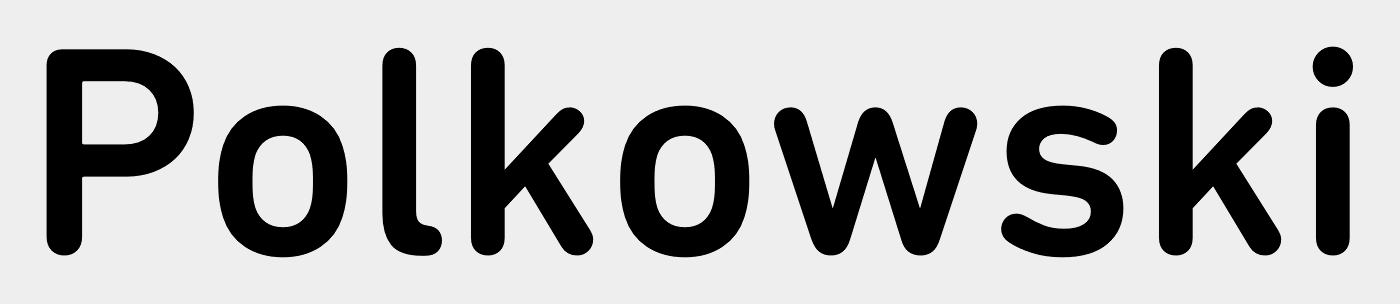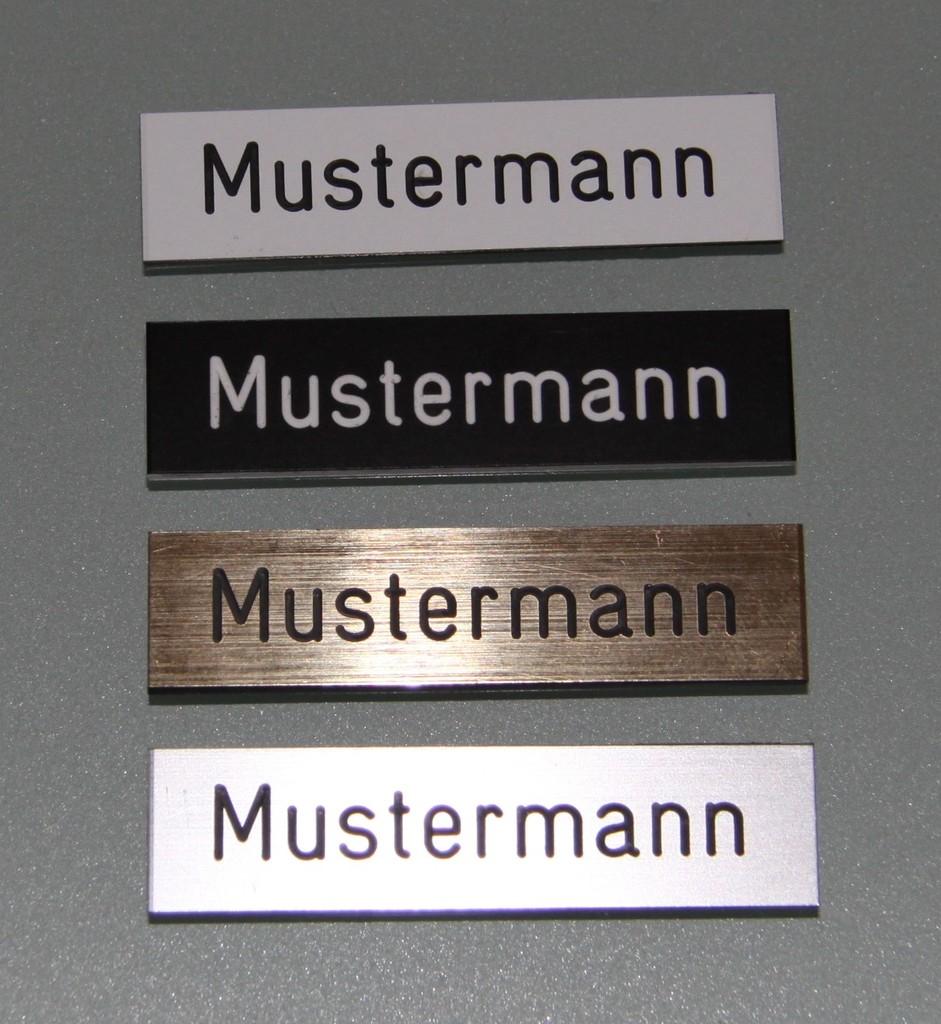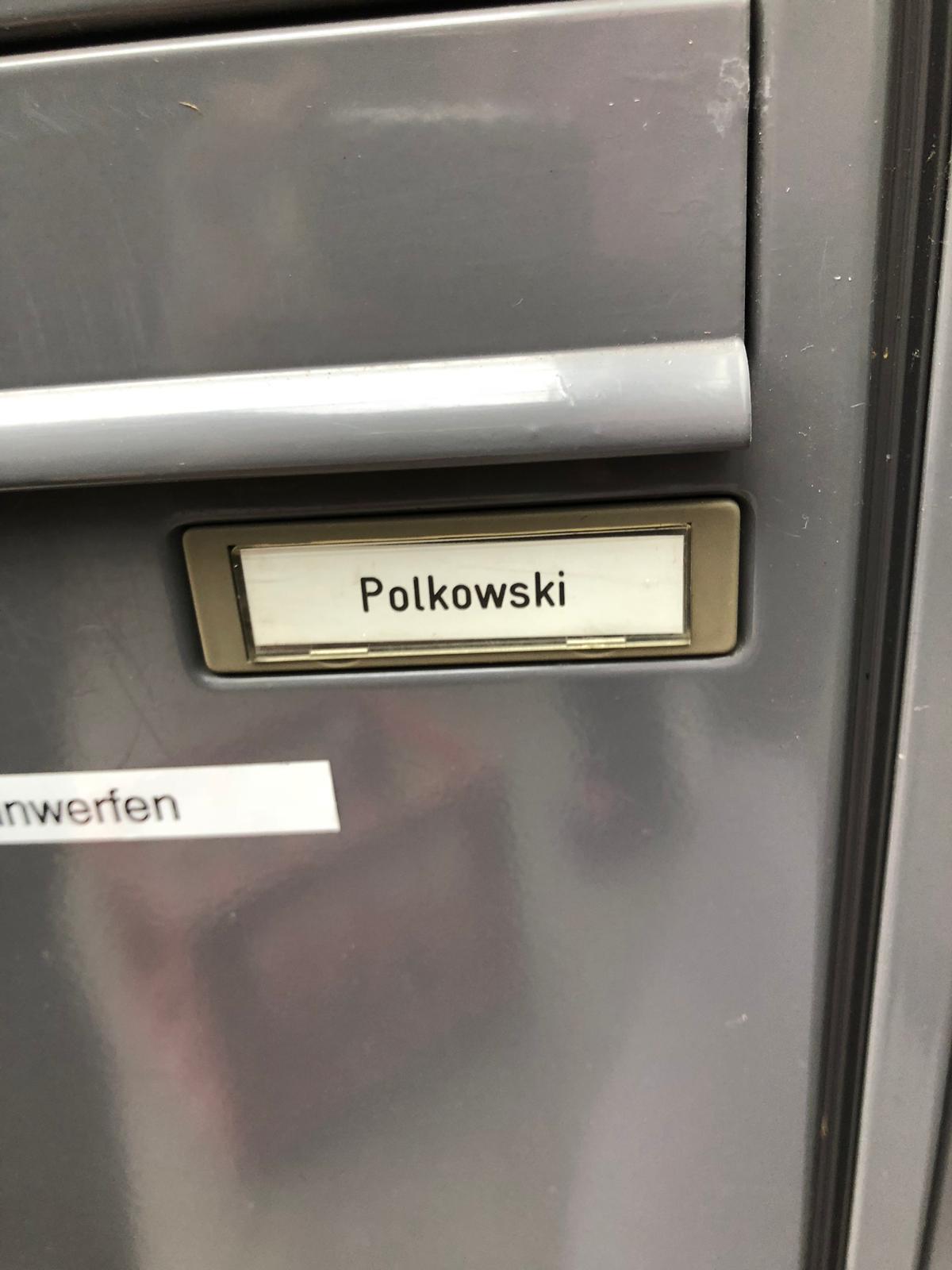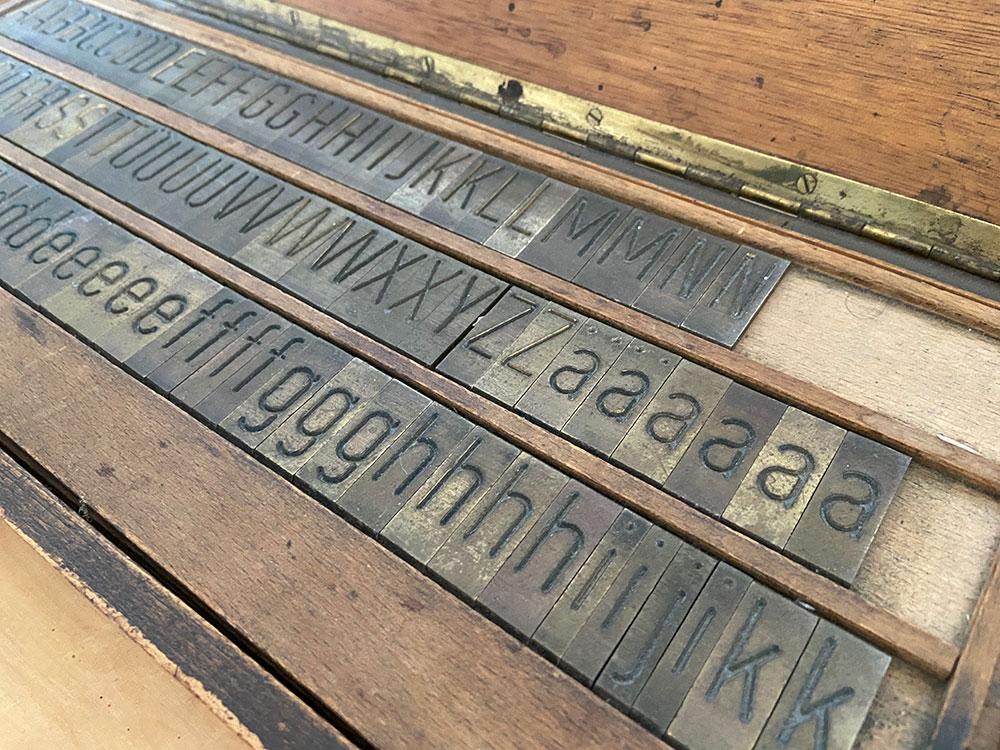
Welche Schrift hat das Briefkastenschild?
ich bin umgezogen und möchte mein Briefkastenschildchen in der gleichen Schrift erstellen, könnt Ihr mir bitte weiterhelfen?
vor 46 Minuten schrieb Dagmar:
möchte mein Briefkastenschildchen in der gleichen Schrift erstellen
Einfach zum Mister Minit (oder wie die Schuster, Graveure und Schlüsselnachmacher bei dir auch immer heißen) und anhand des Musters herstellen lassen. Die haben genau diese "Schrift" schon in ihren Graviermaschinen.
das sind sehr wahrscheinlich keine Schriften im üblichen Sinne, wie wir sie vom Rechner kennen. Das sind idR Schriften wie sie mit den Gravourmaschinen mitgeliefert werden. Und dann sind das keine Schriften bei denen die Außenkanten angegeben werden, sondern die Linie auf der der Fräser der Maschine laufen muss, siehe auch den Hinweis von bertel. Für Prägemaschinen gibt es auch sehr spezielle Schriften, welche der von die gesuchten sehr ähnlich sind.
Bei der von Dir und bertel gezeigten Schriften handelt es sich um Schriften die denen nach DIN 1451 sehr ähnlich sind. Die Schritf auf dem Briefkasten ist nahe an der Engschrift nach DIN 1451, also der DIN 1451 Condensed. Man sieht aber beim kleinen a noch ein Schwänzchen, welches die Schriften nach DIN 1451 nicht haben. Das findet man auch öfters bei den Prägeschriften für Blechschilder. Ausfahrt freihalten! Schau da mal bei den häufig Gelb-Schwarzen genauer hin. Dieses Schwänzchen ist bei den typischen grundeten Schriften sehr, sehr selten.
Vielleicht findest Du da eine passende Ersatzschrift? Das Original wirst Du kaum bekommen oder wenn Du es bekommst wahrscheinlich mangels der benötigten Hardware (Fräsmaschine) nicht verwenden können. :baeh:
Wobei das oben auf dem Bild doch ein bedrucktes Zettelchen hinter einer transparenten Kunststoffabdeckung ist, oder? :-?
Aber schon clever, finde ich, dass der Zettelgestalter da ausgerechnet eine Schrift mit Kingelschildgravuranmutung gewählt hat!
"Polkowski" sieht mir schon nach einem gravierten Plastikschild aus, solchen haben wir auch an unserem Briefkasten und der Klingel.
Hi, es ist ein bedruckter Zettel aus Papier hinter Plastikabdeckung.
Dann wurde wohl eine DIN Rounded verwendet.
Und ich würde das alles gar nicht so eng sehen, und bei einem Briefkastenschrift nicht unbedingt die 100% gleiche Schrift anstreben. Grob ähnlich und gut ists. Schließlich muss es ja hauptsächlich vom Briefträger nur lesbar sein. Zudem spielt es ja auch eine Rolle, ob man eine breite oder eine kondensed-Schjrift wählt, wie viel Text da auf den Zettel muss, also ob da eine Familie Li wohnt, oder etwas wie Sabine Leutheusser-Schnarrenberger.
Sicher, wobei andere Schriften da schon auffallen. Bei uns 🇩‍🇪 gab es vor Jahren mal neue Briefkästen (mit integrierten Klingeln). Zuerst waren alle Klingelschilder von der Genossenschaft gedruckt worden, alle in derselben Schrift. Sah prima aus. Schon nach dem ersten Umzug  (und dem ersten Schild in ähnlicher, aber erkennbar anderer, Schrift) sah es spürbar schlechter aus.
Wenn es also nicht zu viel Aufwand macht, fände ich es schon gut, (annähernd) dieselbe Schrift zu nehmen.
Als wir neue Briefkästen bekommen haben, hab ich einfach alle acht neu beschriftet, ehe der Vermieter mir mit Comic Sans oder so dazwischen funkt … nach der Erfahrung der Umbauplanung hätte es bei denen aber auch sicher noch ein halbes Jahr gebraucht, ehe es überhaupt Schilder gegeben hätte … bei uns ist jetzt alles schön in der Skolar Sans :-)
Danke Euch allen für die hilfreichen Antworten. Ein einheitliches Schriftbild ist schon schöner, der Hausmeister wurde bereits gebeten, das Schild zu ändern, doch leider tut sich da nix. Nun helfe ich mir selber, mit Eurer Hilfe, Danke dafür, Dagmar :-D
Du könntest dich auch an die Hausverwaltung wenden, die beauftragt dann den Hausmeister ganz offiziell.
Kommt aber auf die Hausverwaltung an, für wie dringlich – und überhaupt notwendig – die das so halten …
Also bei allen Hausverwaltungen, mit denen ich zu tun hatte, waren die Namensschilder von denen organisiert. Und jetzt bei meiner neuen Wohnung waren die Schilder schon angebracht, als ich zur Übergabe kam. Ich war richtig gerührt :)
Meine 🇩‍🇪 Genossenschaft macht das etwa alle zwei, drei Jahre mal, wenn der Gesamteindruck irgendeinem Verwaltungsmenschen allzu schmuddelig erscheint. Da werden dann auch die »Bitte keine Werbung und keine kostenlosen Zeitungen«-Aufkleber, die fast jeder am Briefschlitz hat, vereinheitlicht. Ein paar Wochen lang sieht dann alles prima aus, bis frustrierte Werbeausträger wieder anfangen, Aufkleber abzupolken. Aber da niemand 2½ Jahre lang unverlangte Werbung bekommen will, kommen dann wieder die selbstgestalteten Schilder.